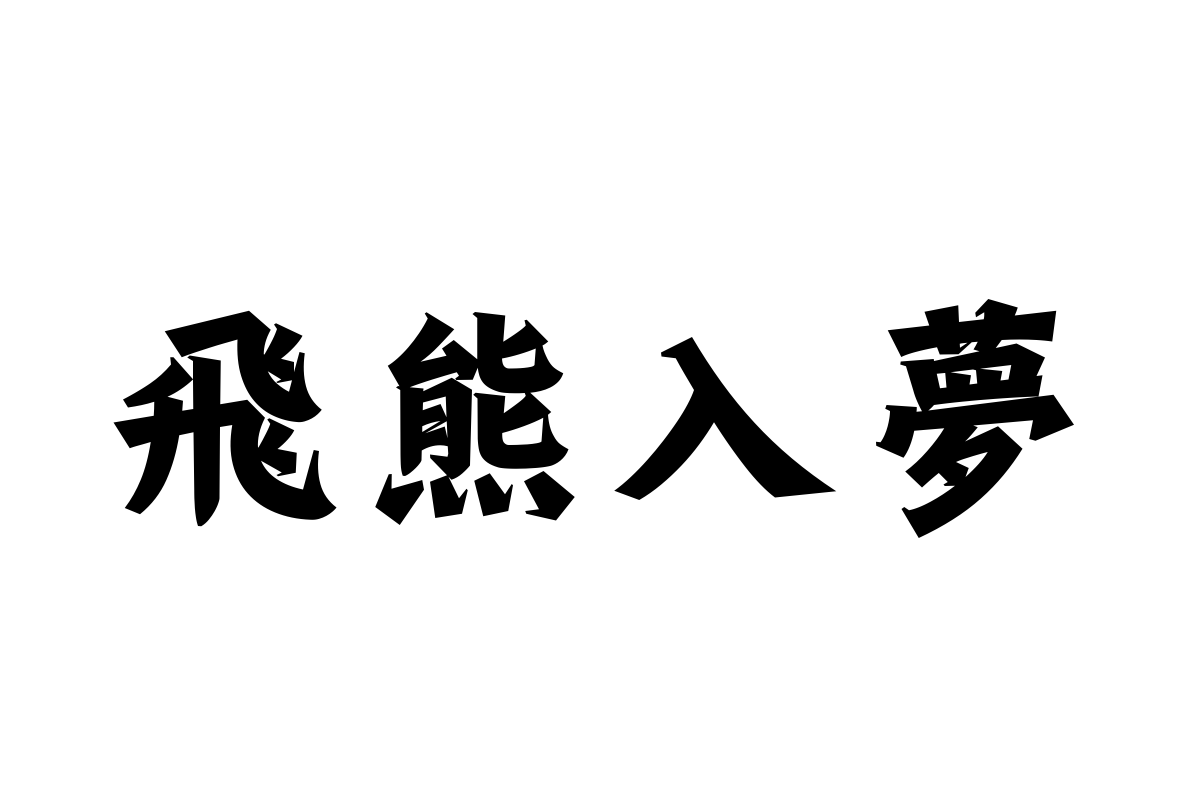
汉仪永字崧黑是一款具有深厚文化内涵的字体,它源自于古代书法艺术的精髓。这款字体以其独特的风格和韵味,展现了汉字书写的魅力和美感。
永字崧黑的特点在于其笔画流畅、结构紧凑,给人一种古朴典雅的感觉。它的线条粗细适中,既有力度又不失柔美,使得每一个字都显得生动而富有生命力。这种特点使得汉仪永字崧黑在视觉上具有很强的冲击力,能够吸引人们的注意力并留下深刻的印象。
此外,汉仪永字崧黑的字形结构也非常独特。它的每个字都经过精心设计,使得整个字体呈现出一种和谐统一的效果。这种设计不仅提高了字体的艺术价值,也使其更加易于阅读和识别。
总的来说,汉仪永字崧黑是一款非常优秀的字体,它不仅能够为设计师提供丰富的设计灵感,还能够为读者带来愉悦的阅读体验。无论是用于印刷还是电子显示,汉仪永字崧黑都能够展现出其独特的魅力和价值。